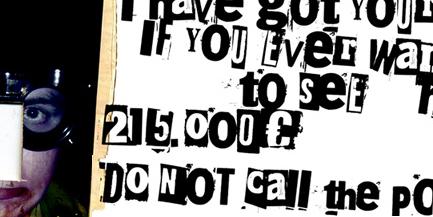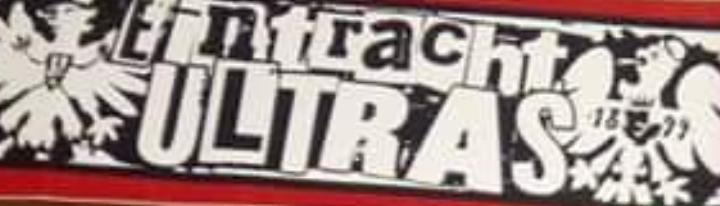
Suche Ultras-EINTRACHT-Schriftart
ich suche die Schriftart welche auf dem Bild zu sehen ist. Diese ist auf einem Aufkleber und wird vermutlich wie dort zu lesen ist den Eintracht Ultras zuzuordnen zu sein.
Die Schriftart muss jetzt nicht unbedingt genau die gleiche sein, sollte aber aufjedenfall sehr ähneln, benötige diese für eine Hochzeit.
das Stichwort lautet Ransom ... Ich wühle da mal duch die Rubriken ...
Leider negativ? Ok, weitersuchen ...
Auf Dafont gibt es diese Rubrik nicht, da findet man diese Schriften unter zerstört ...
Aha? Nach Beliebtheit sortiert findet man dann recht schnell:
215000Euro von junkohanhero
Das Schwarz-Weiß ist invertiert ... ansonsten passt die Schrift.
Er hat auch ähnliche gesucht, daher hab ich ähnliche gepostet ;-)
Alles, was Schwarz ist, Weiß machen. Und umgekehrt.